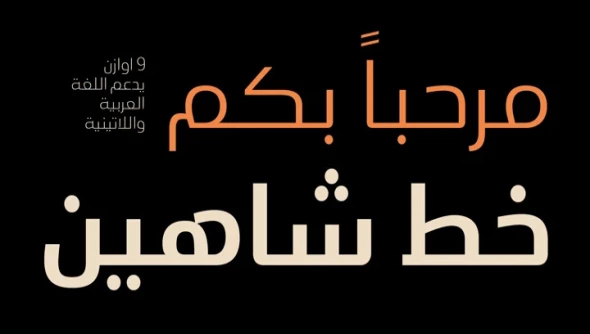
Shaheen Font Family
حول عائلة خطوط شاهين
شاهين هو خط عربي ولاتيني يجسد القوة والميل نحو التوحيد. مع الحفاظ على المظهر الأنيق والبسيط المرتبط به. يشير الاسم أيضًا إلى الطابع القوي للمحرف. شاهين يأتي في 9 أوزان